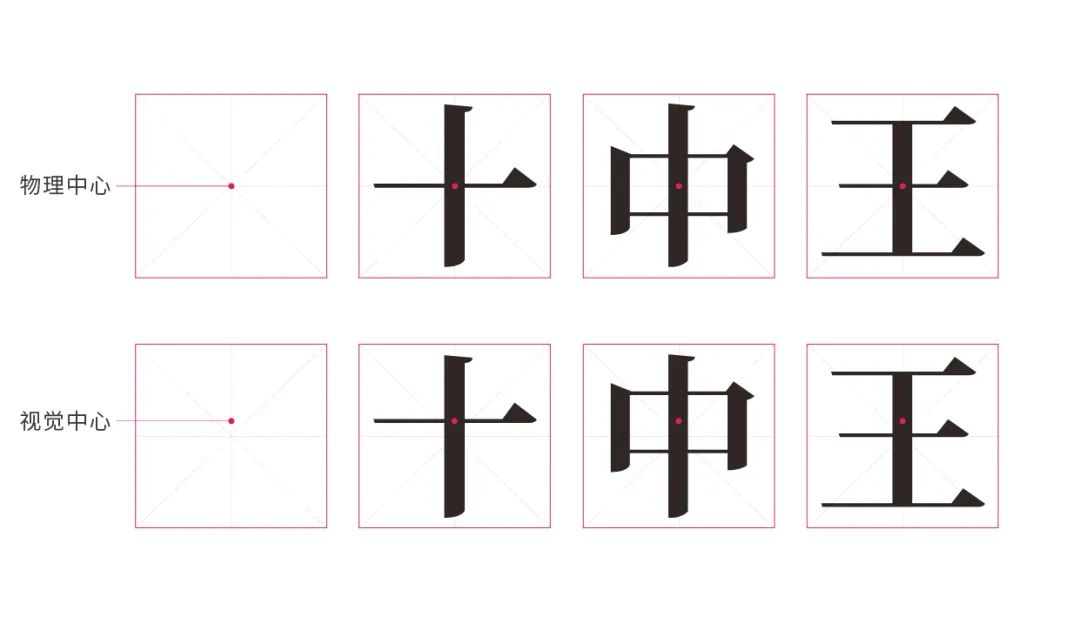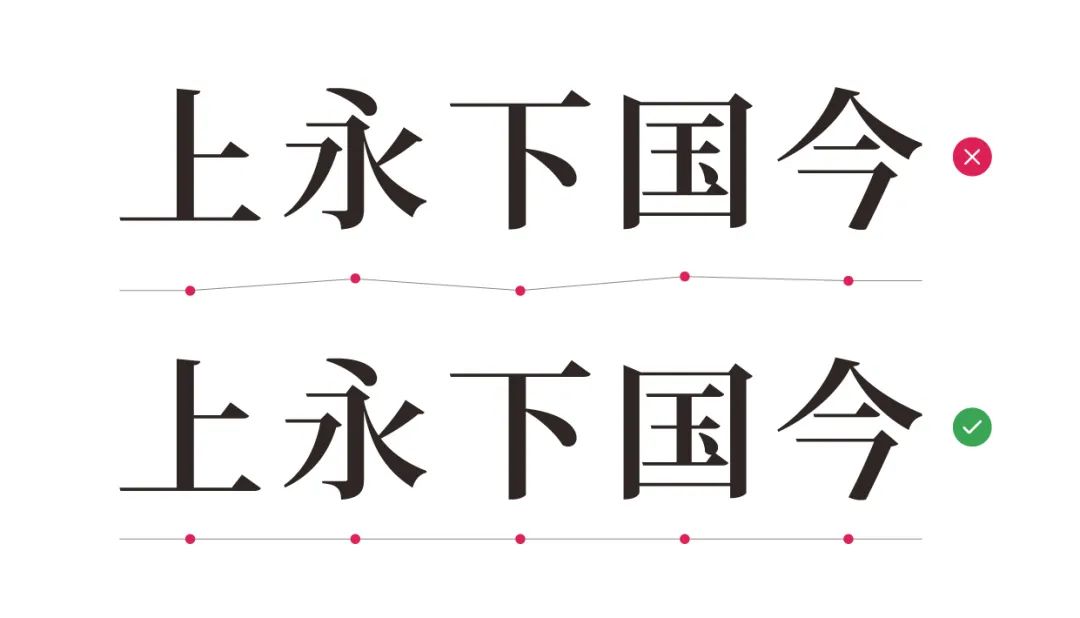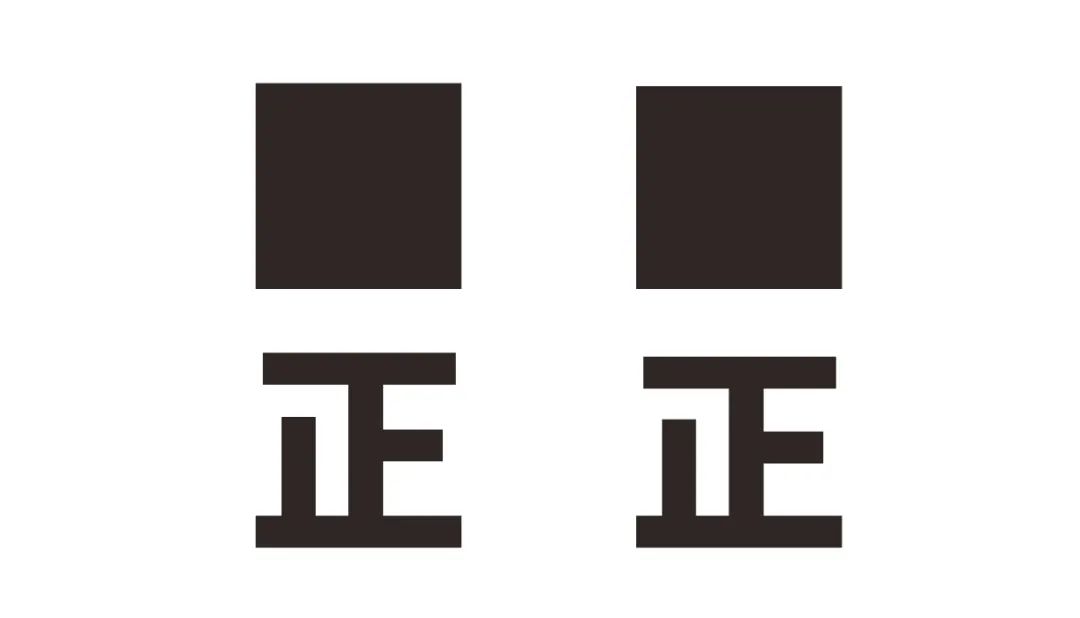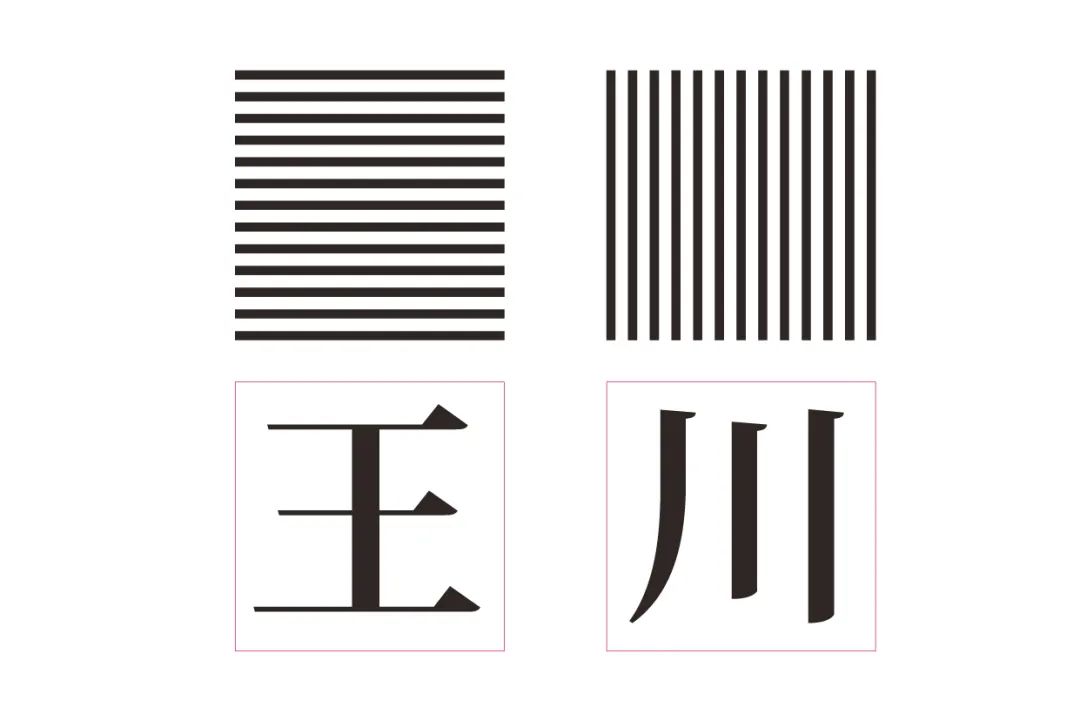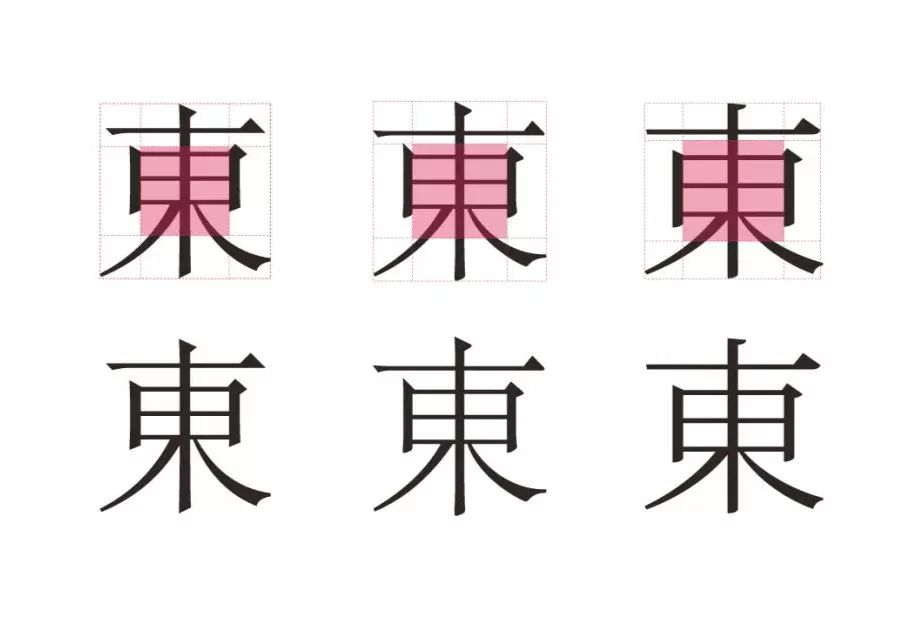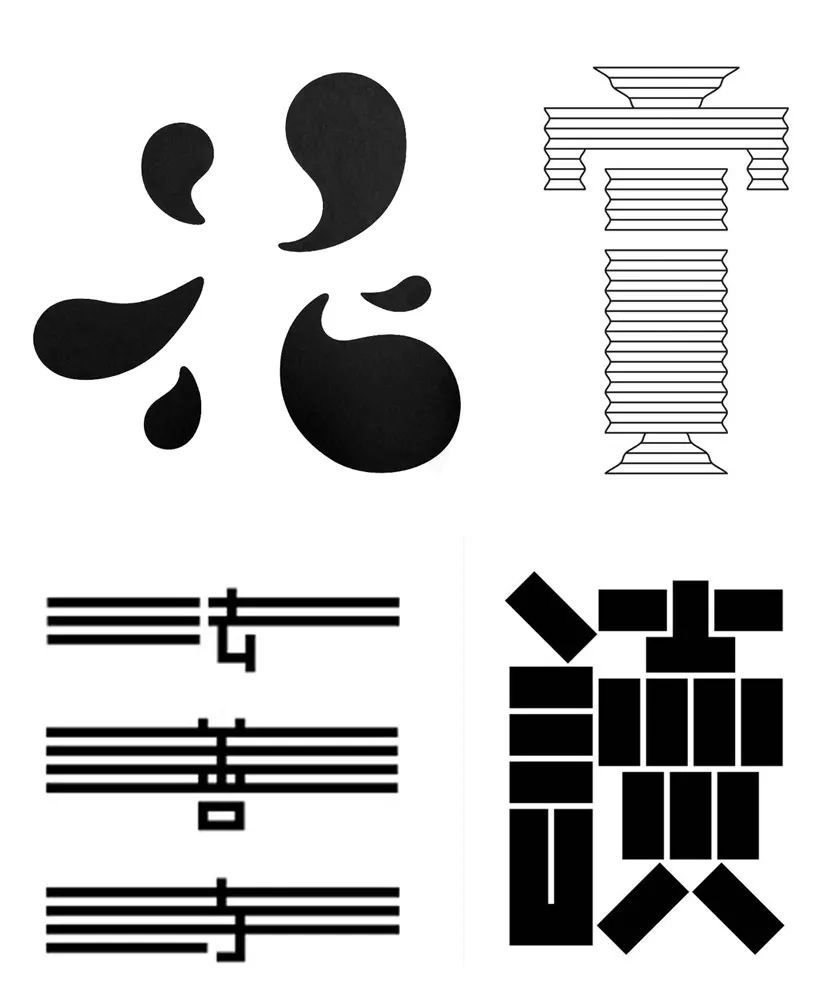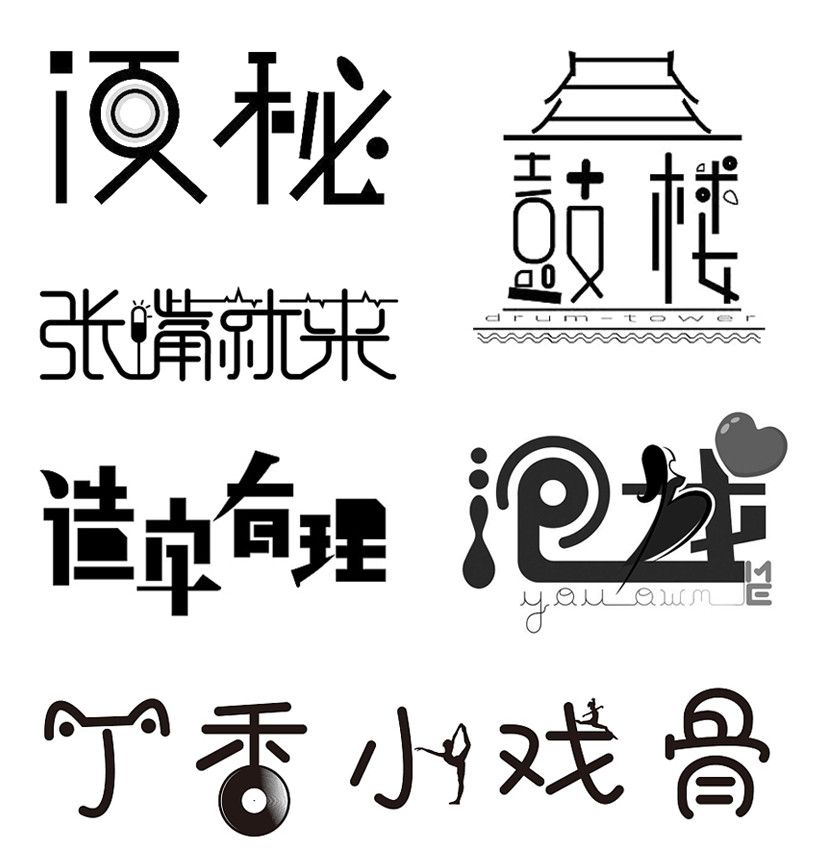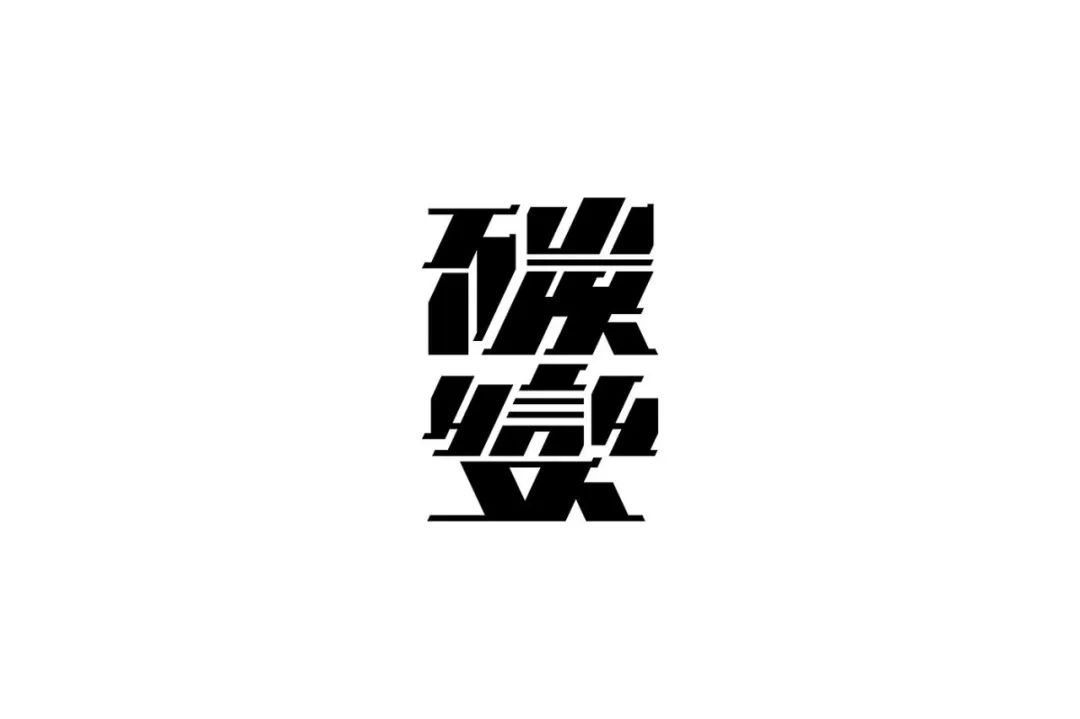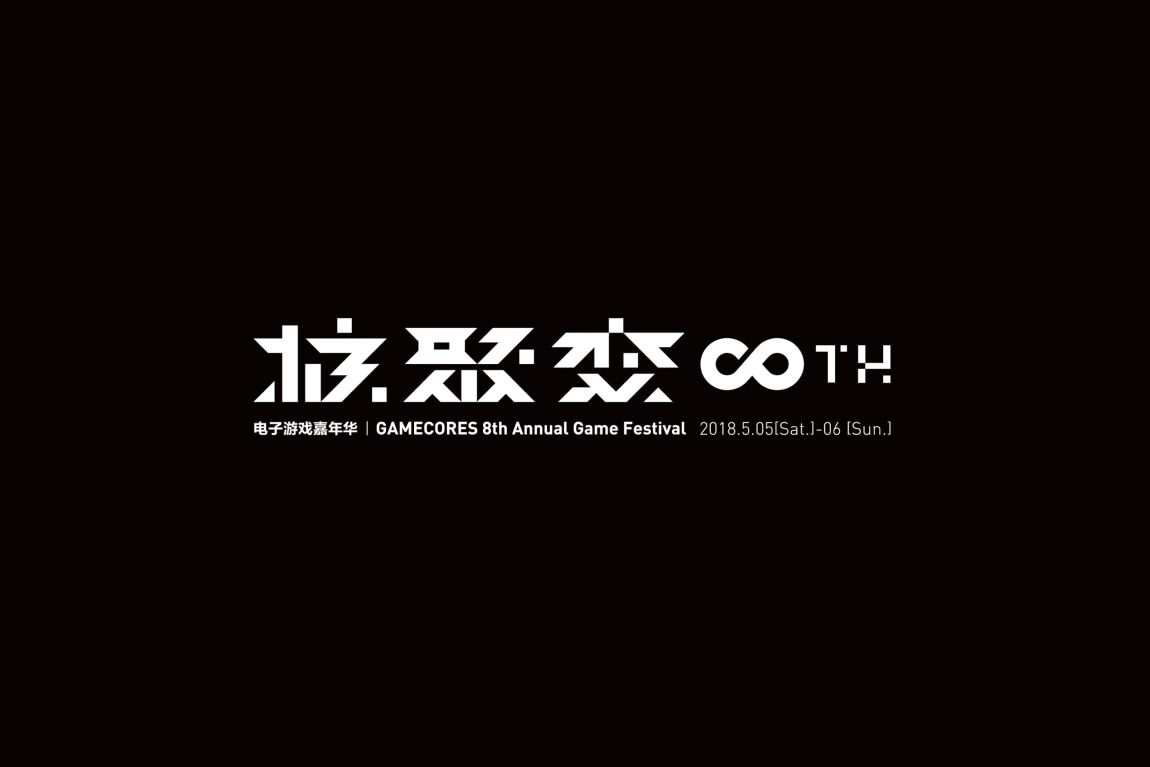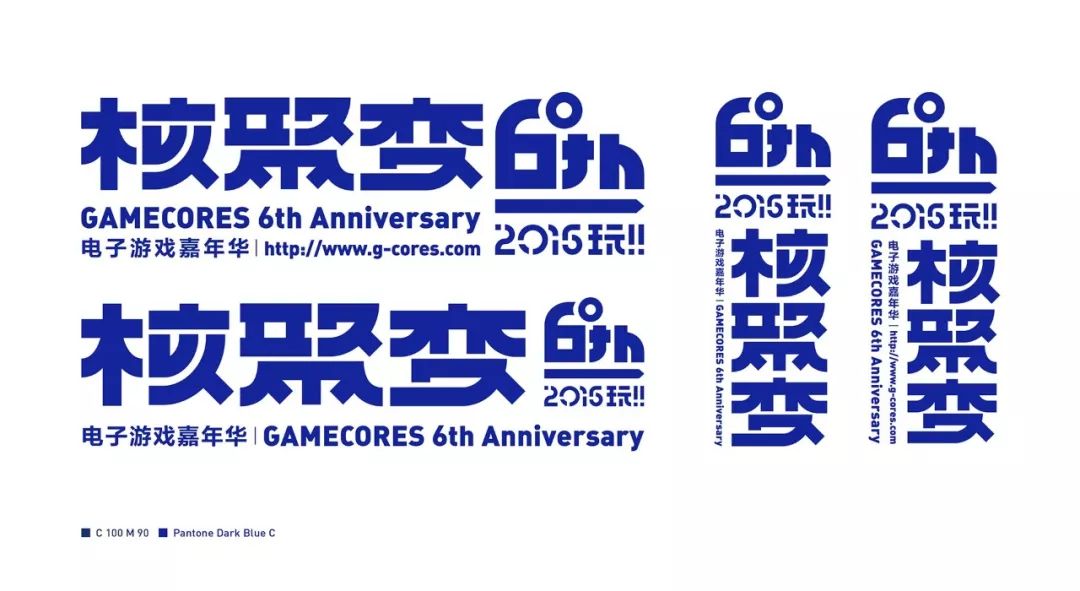
字体设计的基础知识
万物皆有本源,字体也一样,今天我们看到的千变万化、形式各异的字体,都离不开文字本身的根基,脱离了这个根基去做字体,往往难以做出成功的作品,就像练武需要有基本功一样,文字的基础知识对于做好字体,有着不可或缺的作用。
我们常常会看到一些初学者做出来的字体,存在着各种各样的问题,很大原因就是对一些汉字的基础知识不够了解所造成的,接下来我就介绍一些初学者应该知道的关于汉字的基础知识。
【骨骼与体饰】
“骨骼”即字体的内在间架结构,是决定字体内在气质以及是否美观的基础性因素,而“体饰”是字体的装饰,可以影响字体所呈现出来的风格与外观:
下面是几种不同美字的骨架,从以下几个案例可以看出,字体骨架本身就可以呈现出字体内在的气质。
许多初学者容易忽视“骨骼”、沉迷“体饰”,在基础结构没做好的情况下去给字体加很多装饰,这是一个很大的误区。下面这两个案例,就属于过度沉迷“体饰”,忽略了字体本身骨架的反面教材:
▲  忽视“骨骼”、沉迷“体饰”的反面教材
【中心与重心】
物理上绝对的“中心”,人眼看上去却感觉偏低,因为人的眼睛存在视觉错,如果按照物理的中心去设计字体,会让人感觉中间的部分靠下,有往下掉的感觉,这就是为什么大部分字体会把视觉重心放在物理中心点之上的原因,这样更符合人眼的视觉习惯,看上去才会显得舒服。
同时重心的高低会影响字体呈现出来的气质,重心偏高的字体,会显得比较秀气,重心偏低的字体会显得较为稳重。
在设计字体时,要注意整体重心的统一,否则会给人忽高忽低的视觉感受,除非刻意制造高低不同的视觉节奏感,否则一定要将重心统一在一个大致的水平线上,在做用于正文排版的字库字时尤其要注意这一点。
【笔画的粗细】
在设计一款字体时,笔画粗细应当做成一样的吗?答案是不应该,因为字与字之间的笔画繁复程度都不一样,而且同一粗细度的笔画,在横着、竖着、斜着以及变成曲线时,视觉上都会给人粗细不一致的感觉,因为人眼看东西时会存在视错觉,因此在做字的时候,要根据字体笔画的繁杂程度以及视觉感受对笔画粗细进行调整,达到视觉上的统一。下图是一个在物理宽度上完全相等的矩形,它的视觉上的粗细关系依次为:横> 斜 > 竖 > 曲。
也正因为如此,大多数字体在设计时都遵循横细竖粗这一原则。除了横细竖粗之外,字体设计时还应遵循”繁细简粗、内细外粗、副笔细主笔粗”的设计原则:
【字面大小】
一个边长完全相等的正方形,看上去却显得有些偏高,这依然是视错觉的影响,因此通常做正方形的字,都要把外框压扁一些,消除视错觉的影响。下图左为物理正方形,右为视觉正方形。
有些同学会想,既然是方块字,那做的时候就画几个同等大小的方格子,每个字的最外侧笔画都顶着方格子的边框做,这样就统一了吧?如果按照这种思路,我们设计“口语”这两个字,就会是下面这张图的结果:
显然,这种思路是错误的,汉字虽然是方块字,但其笔画构成的外形是千变万化的,一般认为汉字最典型的外形几何特征可分为4种类型:方形、圆形、菱形、三角形。方形最大,菱形最小。如果细分的话汉字的外形能够对应到15种甚至以上的几何图形,如方形、长方(站立)、长方(横躺)、圆形、正三角形、梯形、倒三角形、菱形、五边形……等等。因此面对不同形状以及笔画的粗细多寡,我们需要根据视觉原理去调整它们的大小,以达到视觉上的平衡。
在我们固有的意识里往往认为笔画越多的字会显得越大,实际上却正好相反,笔画多的字在视觉上会显小,因为它的负空间被分割的很碎、很小,而笔画少的字负空间很大,所以视觉上就会显得大,也正因为如此,笔画越少的字在设计的时候就越要压缩。
在设计以横笔为主的字时应上下压缩一些,左右加宽一些,设计竖笔画为主的字时则正相反,这是因为在两个同等面积的正方形内画满等距的横线与竖线,横线一组在视觉上会显瘦高,竖线一组会显扁矮。
【汉字的中宫】
中宫,顾名思义,就是指汉字九宫格中心那一格的区域,中宫的大小会影响字体呈现出来的气质以及字体在极端环境下的可识别度,通常中宫偏小的字体气质上显得比较清秀,但在字体较小或远距离识别上体验较差(如屏显字体和高速路牌字体),中宫偏大的字体气质上显得稳、拙一些,而且由于内白空间较大,因此识别性上优于中宫偏小的字体。
下图为日本高速公路字体与普通黑体的对比,明显中宫偏大的左侧字体识别性高于右边。
以上所讲理论知识,更多是针对用于大面积排版的字库字体,以及字形偏传统的字体设计,对于追求创意性和独特性的字体,如品牌LOGO字体、营销活动主题字体及海报标题字体等需要较强创意性、形式感较强的字体,以上理论并不完全适用,但也绝非无章可循,接下来讲一下这类型字体需要遵循的一些基本原则。
【形式语言的统一】
统一的形式语言是做好设计的基础,这一点在现代的艺术邻域中被一再印证,不论是绘画、建筑、海报、工业设计等都能看到统一形式语言的经典案例。
▲ 日本艺术家草间弥生,将圆这一形式发挥到了极致
▲ 梵高和蒙德里安的作品,都运用了统一的形式语言
▲ 经典的建筑作品同样是因为形式语言的统一性
▲ 福田繁雄海报作品,每一张的形式语言都很统一
▲ 戴森的产品之所以高级,也是因为统一的形式语言
回到字体,我们来看一些大师的作品,和上面所举的例子原理是一致的,运用统一的形式语言去设计字体:
再来看一些形式语言不统一的反面教材:
这些字体之所以看着别扭,其中一个重要原因就是形式语言的混乱,在一个字体设计中加入了N多不相干的形式,所以就很难形成美感。所以在设计字体的时候,尤其是初学者,一定要保持形式语言的纯粹和统一,不要什么元素都往上加。
【正负形空间的均衡】
无论是偏向传统的字库字体还是偏向创意的美术字,都需要注重正负形空间的均衡和美观。
初学者常常忽略掉负形空间,但其实对负形空间的设计才是最重要的,德国字体设计大师ErikSpiekermann曾经说过:“重要的不是设计黑的部分,而是设计白的部分”, 只有负形空间的均衡,才能造就正形空间的美观和舒适。
如果不注重负形空间,就难以做出好看的字体,下面这个案例就属于负形空间没有做好,因此整个字体看上去很不舒服:
▲ 负形空间没做好,字体给人的感觉就会比较别扭
将负形空间优化后,字体的观感会好很多:
在设计字体的时候,每一笔的笔画曲直、倾斜角度、饰角形状等都要考虑与周边笔画所形成的负形空间是否美观,不要盲区去变形或添加装饰,这一点初学者一定要注意。
【创意字形的基本思路】
除了传统字形外,我们设计创意字形,有一个最基本也是最常见的思路,就是几何化,即把原有的带有书写特征的笔画用几何形去替代,这是非常普遍的一种设计字体的方法。
以上这些案例是将笔画做了几何化处理,还有更加纯粹的几何化,是将偏旁部首整体做几何化处理,字体的创意性和形式感会更强:
用这种思路做字的案例非常多,这里就不列举了,总之几何化是做字的一种很重要的思路,对于设计师来讲一定要掌握。
当然,几何化的做字思路本质上是一种做减法的设计思路,这是我建议初学者去首要学习的方向,因为我常常看到初学者喜欢用加法设计字体,就是喜欢不断的往上加装饰、加特效,看起来好像很唬人、貌似很有 “设计感”,其实则离本质的东西越来越远,加法看似简单,其实要做好非常难,因为加的东西越多越考验你的控制能力,因此不建议初学者往加法的方向去走。